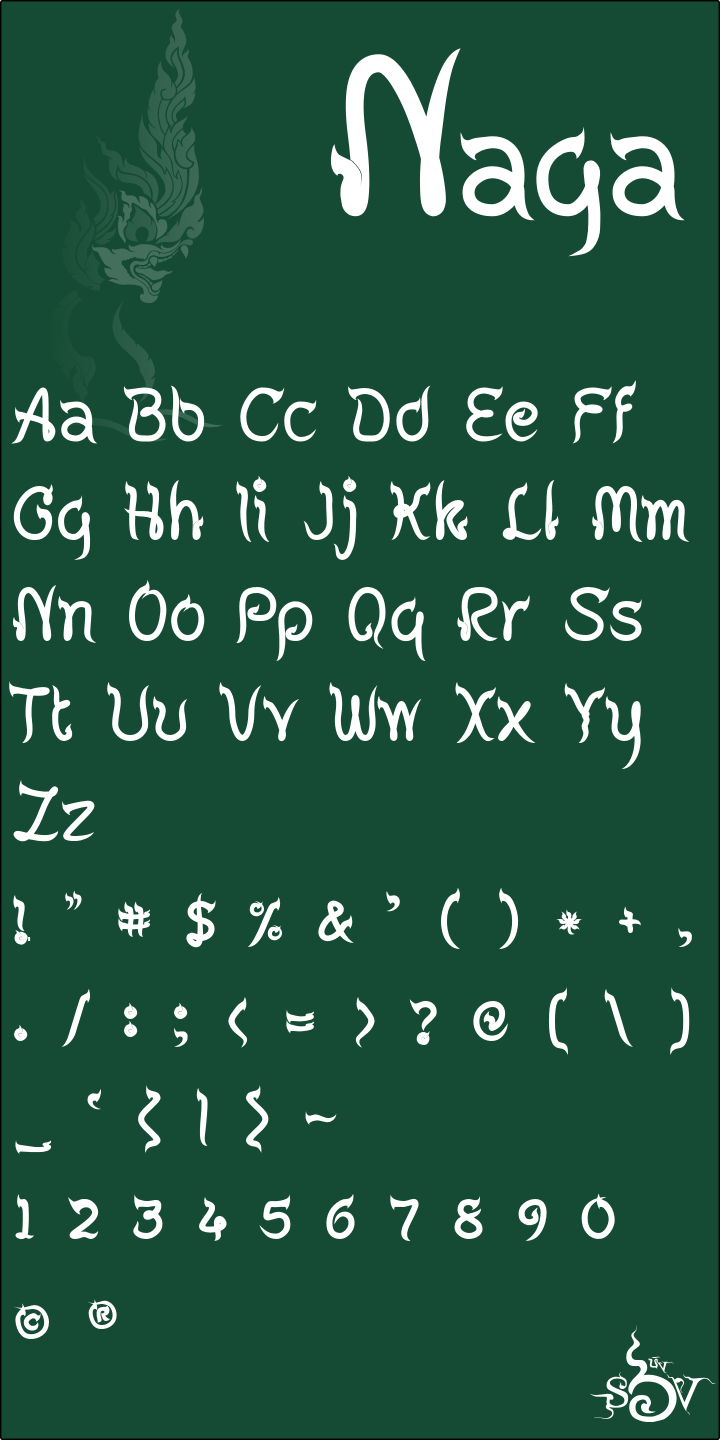
ฟอนต์นาคา
ชื่อฟอนต์ : นาคา (SOV_naga)
ฟอนต์ลายไทยชุดที่ 2 นำประสบการณ์จากฟอนต์นพมาศ มาปรับปรุง
1. ปรับหัวตัวอักษร เป็นแบบเชิดขึ้น พอร่างออกมาแล้วนึกถึงพญานาค จึงทำเป็นรูปพญานาค
2. ลดทอนรายละเอียดลงเพื่อให้เรียบง่ายขึ่น แต่ยังคงพอดูออกว่าเป็นพญานาค
3. จัดช่องไฟให้เหมาะสม กลมกลืม  รวมทั้งภาพรวมเวลานำตัวอักษรมาอยู่รวมกัน
4. นำแนวคิด อ.ธงชัย ศรีเมือง เรื่องการผสมฟอนต์ 2 type face มาใช้  เพื่อให้ภาพอักษรที่เขียนออกมาหลากหลายขึ้น แม้จะเขียนคำเดียวกัน
5. ทดลองแก้ไขปัญหา สระโอ สระไอ สระใอ ให้หลบสระ วรรณยุกต์ของตัวอักษรข้างหน้าได้